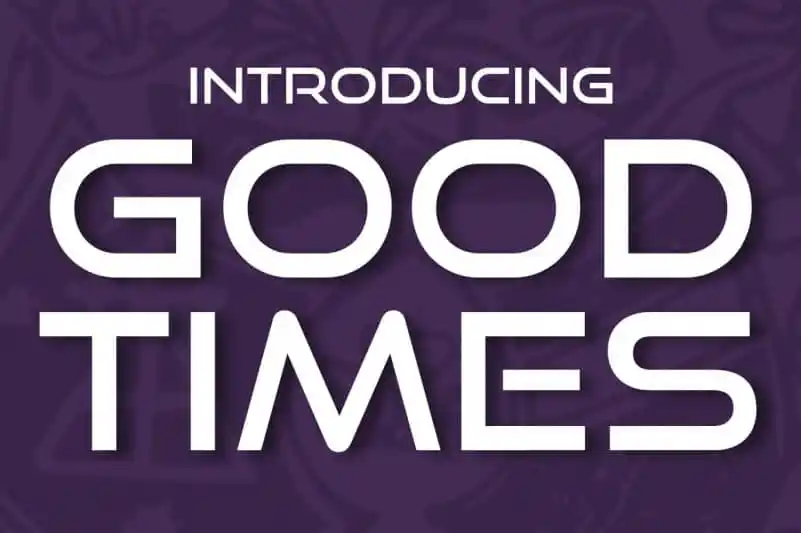
A Good Times Sans Serif Font é uma escolha ideal para quem busca expressar simplicidade e modernidade em projetos digitais. Originalmente criada em 1998, a fonte foi revisada no ano de 2008 com um enfoque ainda mais cuidadoso na personalização. As atenções aos detalhes agora incluem maior número de idiomas, tornando-a perfeita para a criação de aplicativos internacionais. Agora, Good Times também oferece uma ampliação em termos de recursos, incluindo fracionários e ordinais numéricos. Estes detalhes adicionais podem ser úteis quando usada em aplicações OpenType avançadas, pois as combinações de letras comuns são automaticamente substituídas por pares personalizados para um efeito visual mais realista, que pode ser comparado a uma impressão embutida. Essa funcionalidade torna o texto ainda mais atraente e elegante em projetos digitais.